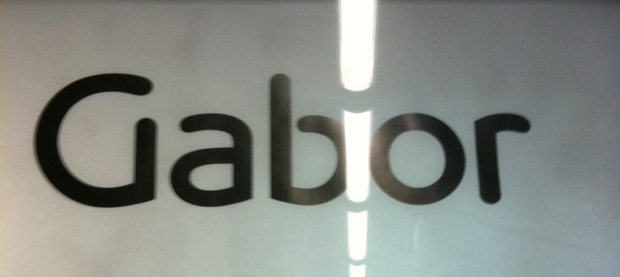
Ich suche eine Schrift. Wer kann helfen?
Wer kennt die folgende Schrift?
Hallo :-) Ich vermute ganz stark, dass die extra für Gabor gezeichnet wurde und keine normal erhältliche Satzschrift ist.
Das sieht so ein bisschen so aus, als hätte einer die Phoenica und die Benguiat in einen Topf geschmissen und ordentlich gerührt ...